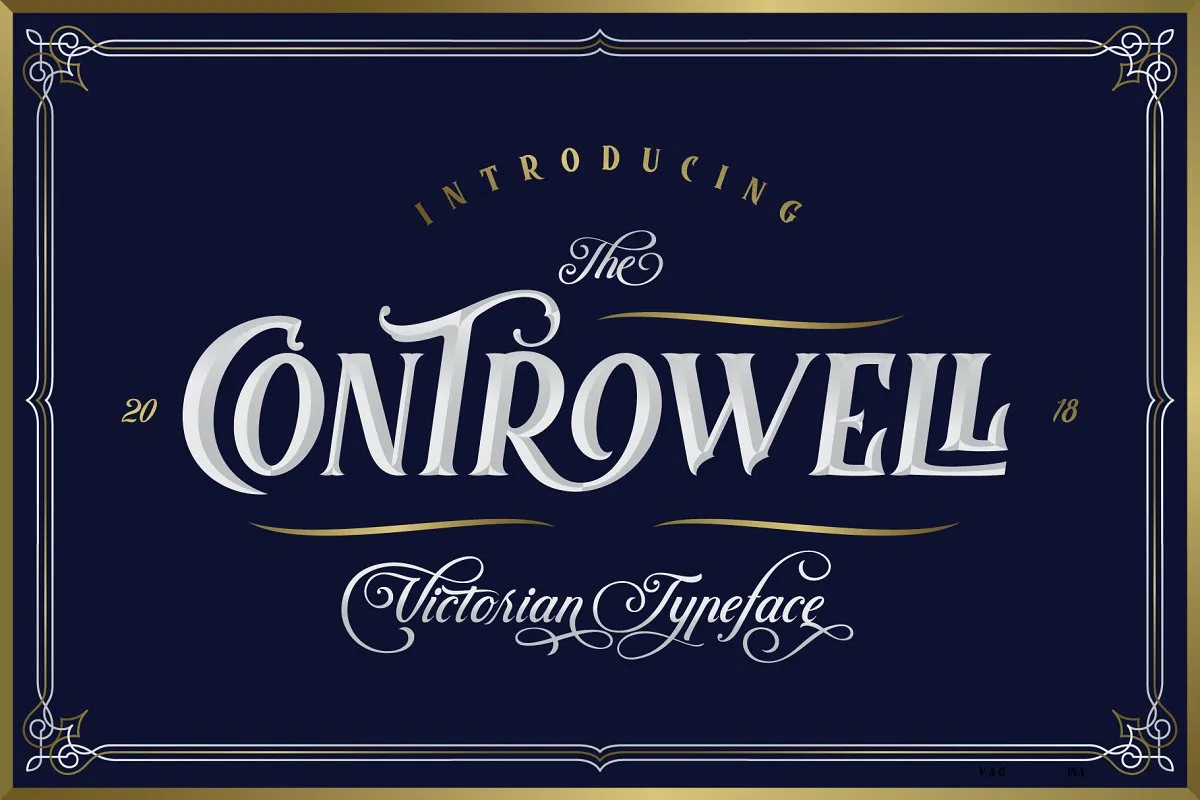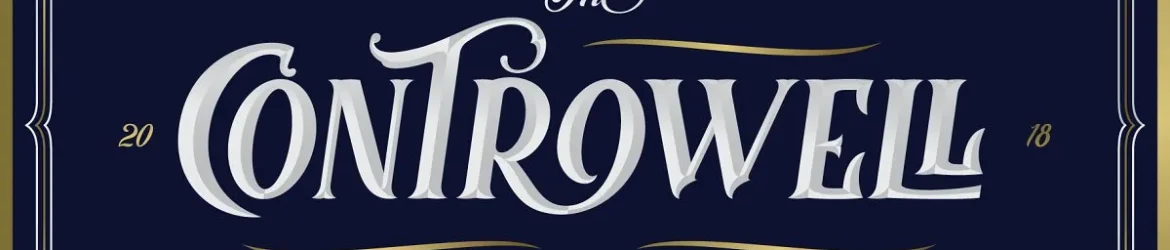
Controwell Victorian Typeface – Download Grátis
Estamos entusiasmados em apresentar a vocês o Controwell Script Font, uma nova opção para sua coleção de fonts script. Este especializado na tipografia serifada e script, é perfeito para um amplo range de projetos de design gráfico, desde logotipos até capas de livros vintage. A fonte Controwell Typeface apresenta uma estética única com duas camadas que dão uma sensação de metallicidade cool. Além disso, oferece alternativas personalizáveis para cada caracter, garantindo a combinação perfeita com sua paleta de cores e estilo visual. Um dos benefícios mais interessantes deste fonte é seu uso versátil em diversas aplicações gráficas. Seja você um designer que busca criar identidades visuais sofisticadas, ou aquele que está buscando uma maneira criativa de personalizar embalagens de produtos de consumo, este fonte pode ser sua solução. Além disso, o Controwell Script Font é especialmente apropriado para trabalhos como etiquetas de cerveja, rótulos de vodka e whiskey, criação de posters inspirados em estilos vintage, ou capas de livros com um toque Victoriano. Em resumo, este é um ótimo recurso para qualquer designer que procura uma fonte script atraente e versátil que pode transformar seu design em algo realmente memorável.